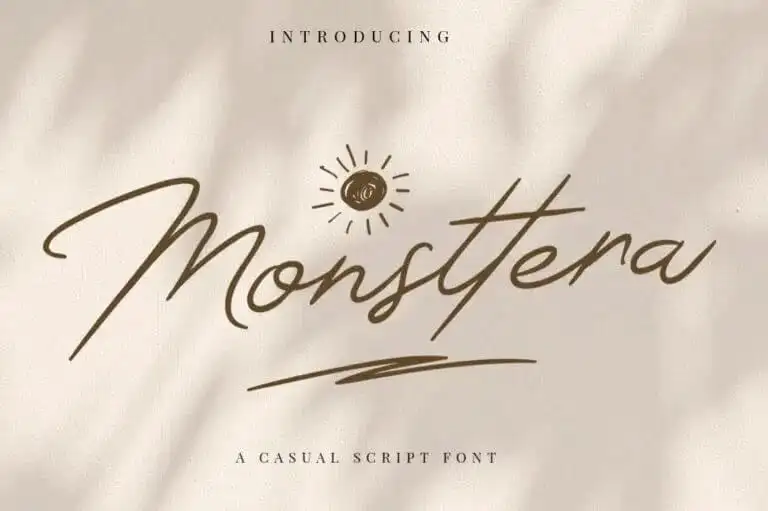
Monsttera Handwritten Font
Monsttera Handwritten Font é uma elegante fonte escrita a mão moderna criada para tornar seu texto ainda mais sofisticado e inovador. Como sua própria descrição original menciona, foi projetada para imitar a aparência de um script escrito à mão naturalmente possível, incorporando alternativas minúsculas, ligaturas e sublinhados para proporcionar uma experiência visual próxima do real. A Monsttera Handwritten Font é perfeita para quem deseja dar um toque único e autêntico a seus projetos digitais. Seja em cartazes de lojas, logotipos para marcas ou texturas interativas nos websites – essa fonte oferece a oportunidade de criar um design que se destaca na sua comunicação visual. Ela é a escolha perfeita para quem valoriza tanto a modernidade quanto o charme do estilo tradicionalmente escrito à mão. Ao adquirir Monsttera Handwritten Font, você não apenas adquire uma ferramenta de design imprescindível, mas também um passo além na sua capacidade de expressar seu próprio estilo visual. Com sua versão criada por designers talentosos da plataforma 99designs, esta fonte é uma escolha segura para quem busca qualidade e consistência em seus projetos digitais.